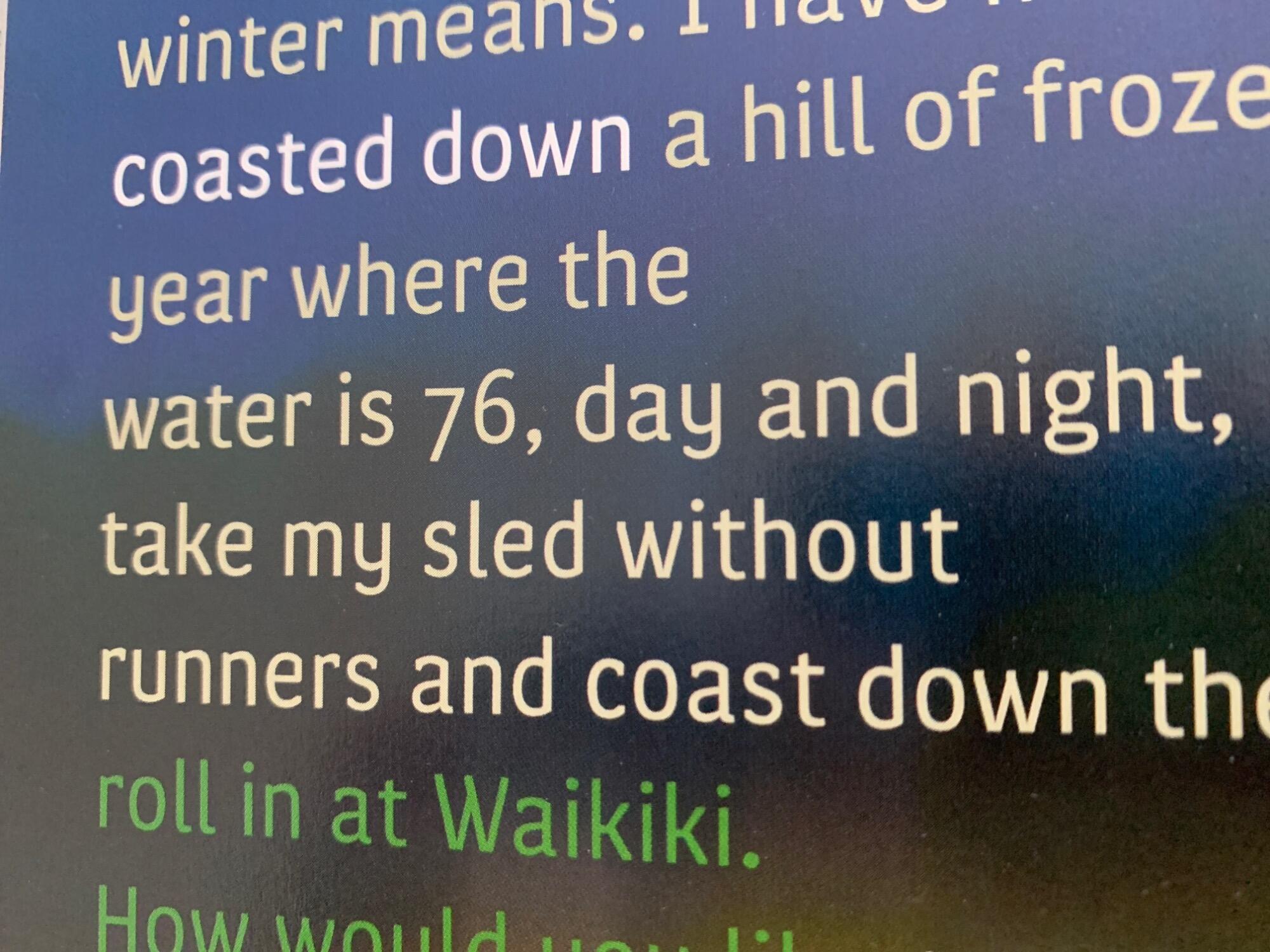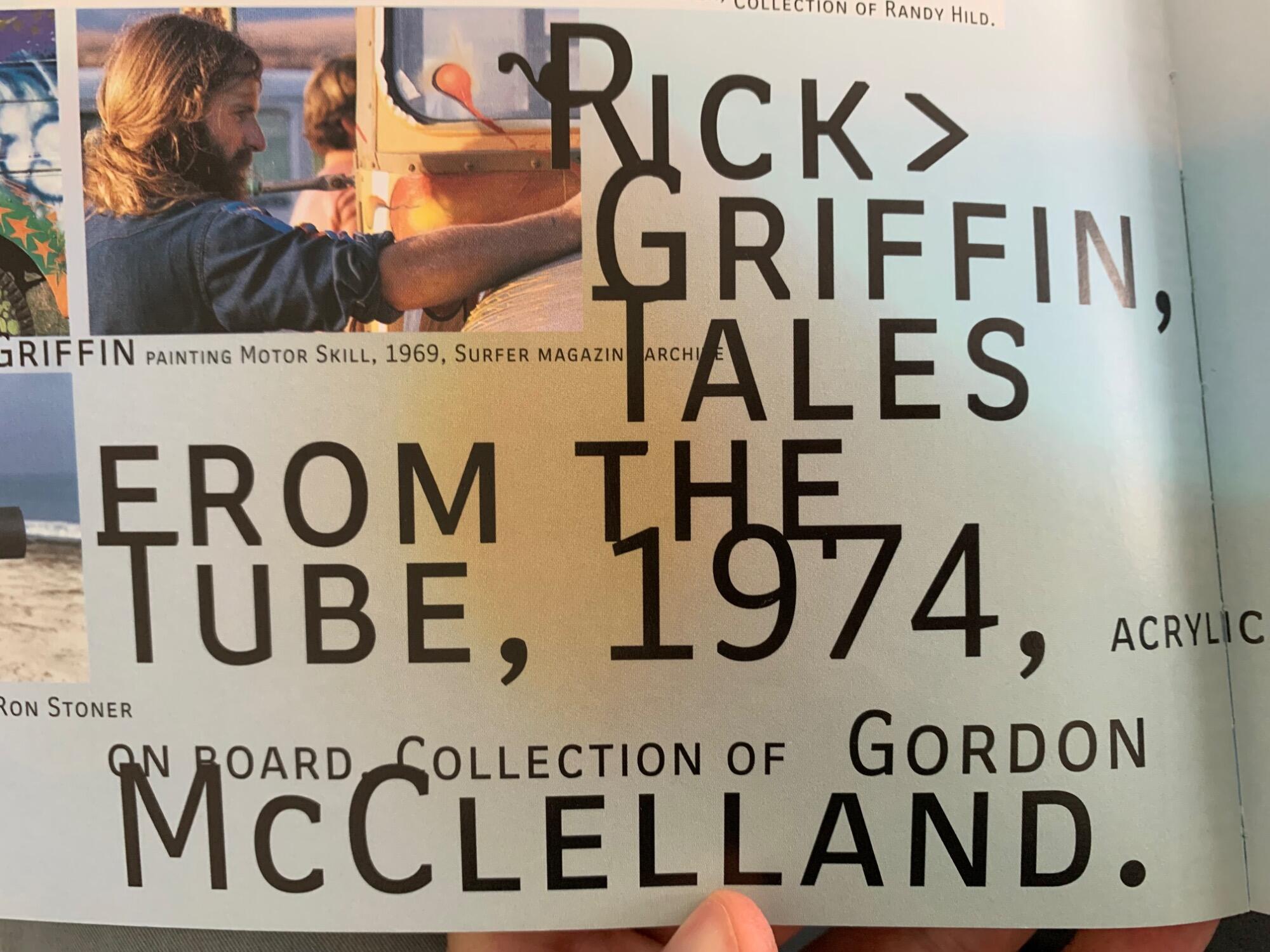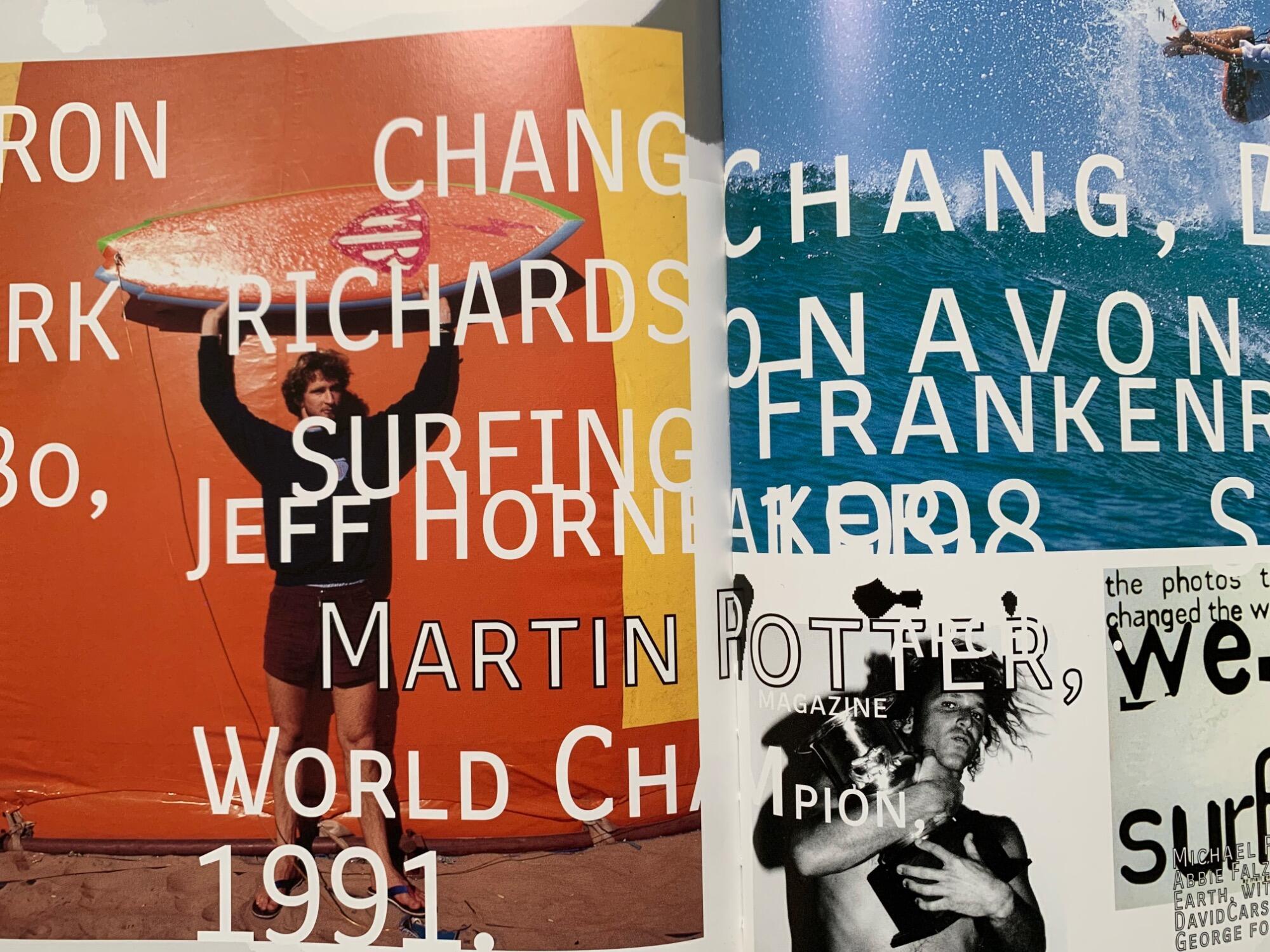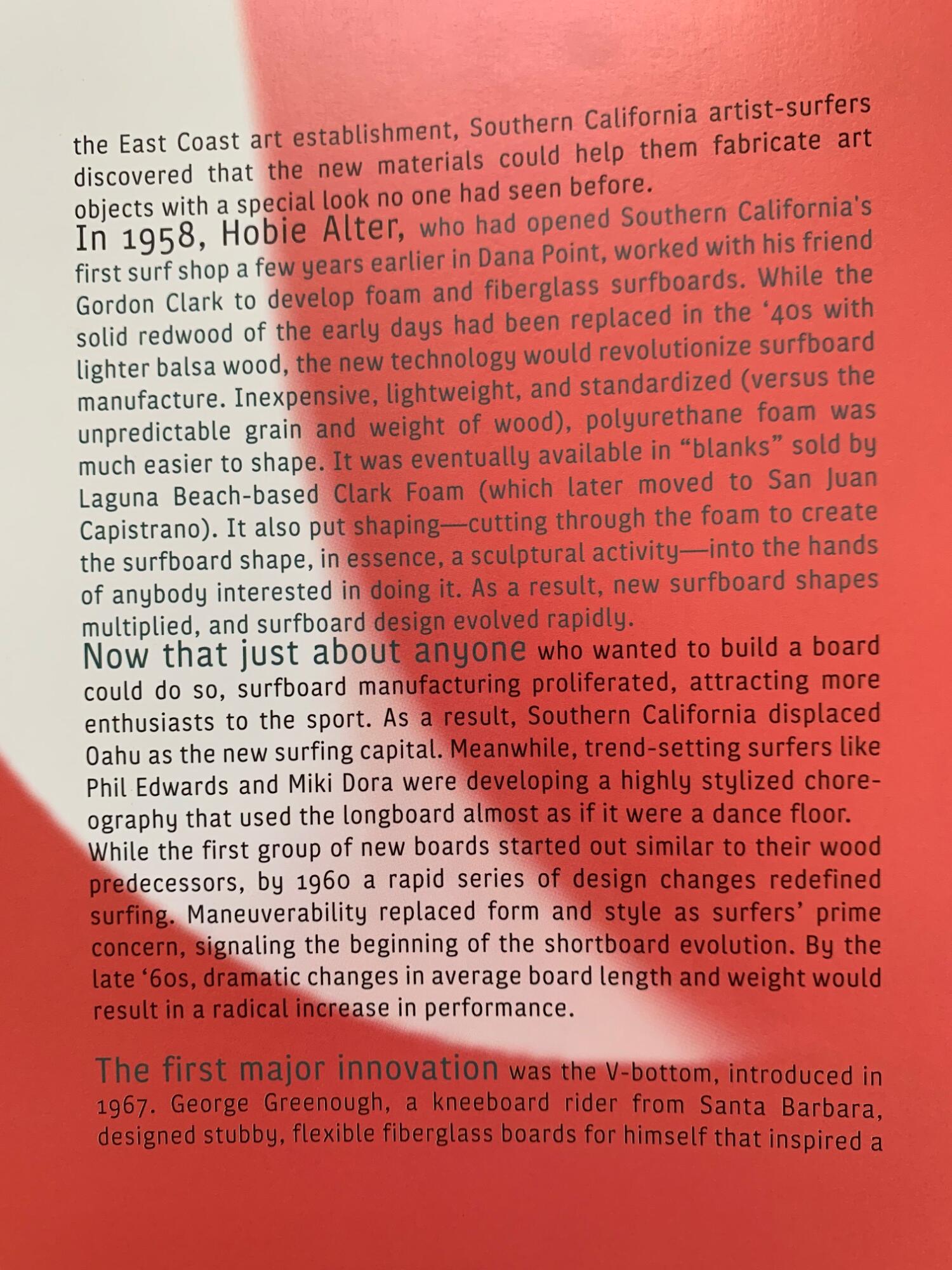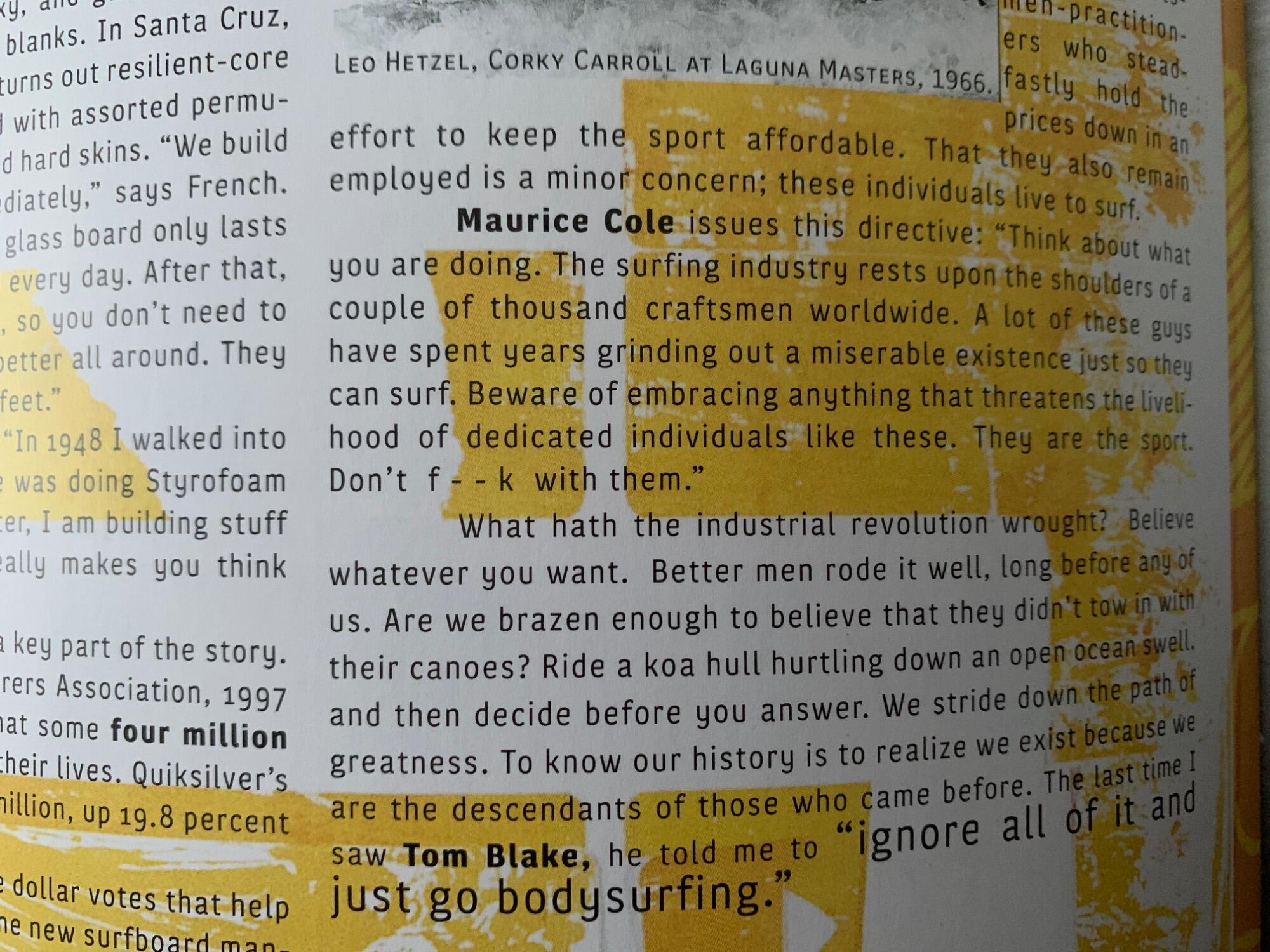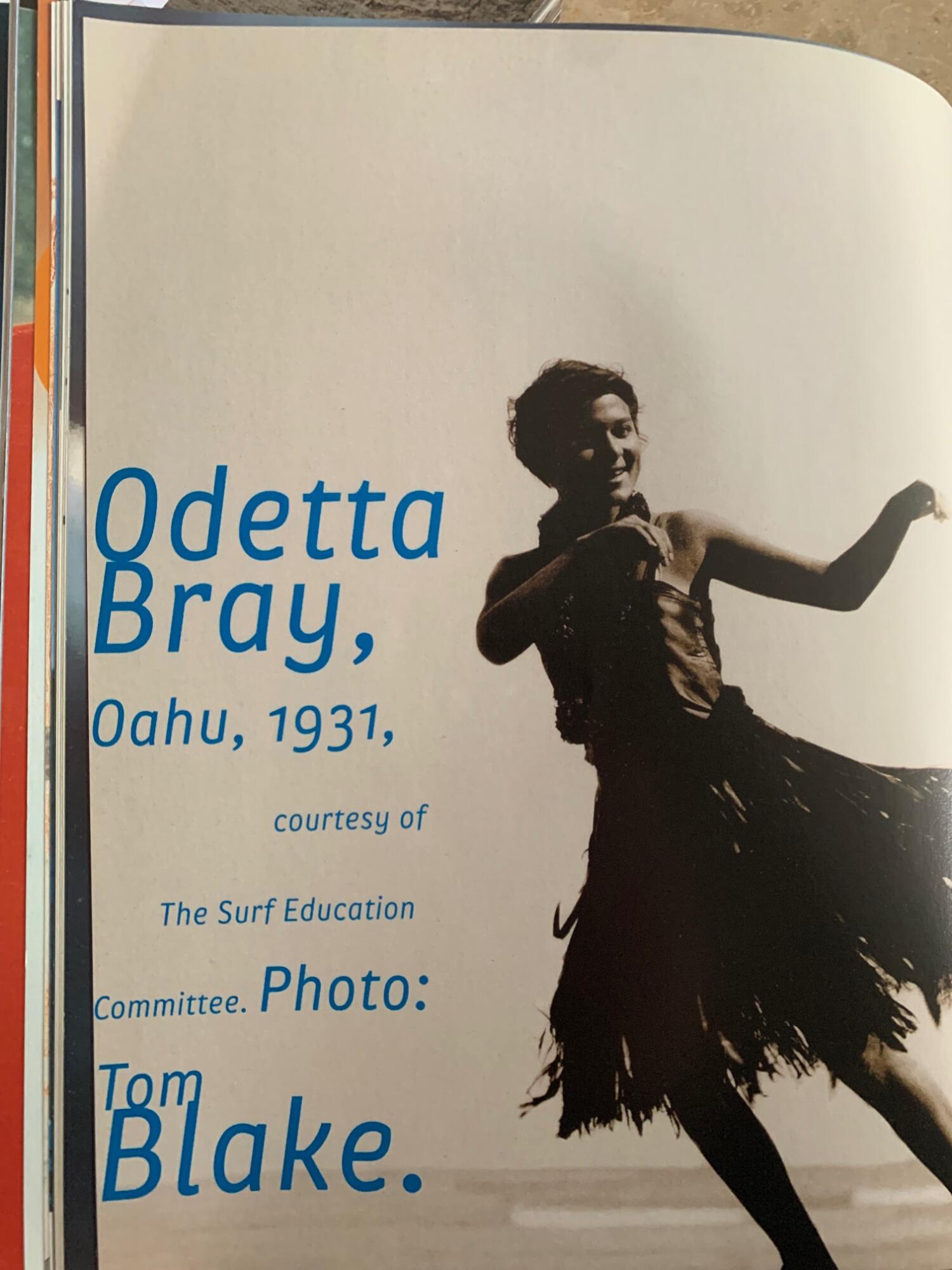
Schrift aus „Surf Culture“
Die Publikation stammt aus dem Jahr 2002, erschienen im Gingko-Verlag
in Zusammenarbeit mit dem Laguna Art Museum. Design von David Carson.
Nach langer Suche hier die Frage: In welchem Font ist sie gesetzt?
Leider ist im Impressum nichts zu finden.
Customized – das dachte ich auch.
Aber krass ist ja, wie weit ausgebaut die Schrift ist: Echte Kapitälchen, Sonderzeichen, sogar Mediävalziffern und neben Regular auch noch in Bold.
Das Ganze individuell zu bauen, wäre schon ein ziemlicher Aufwand.